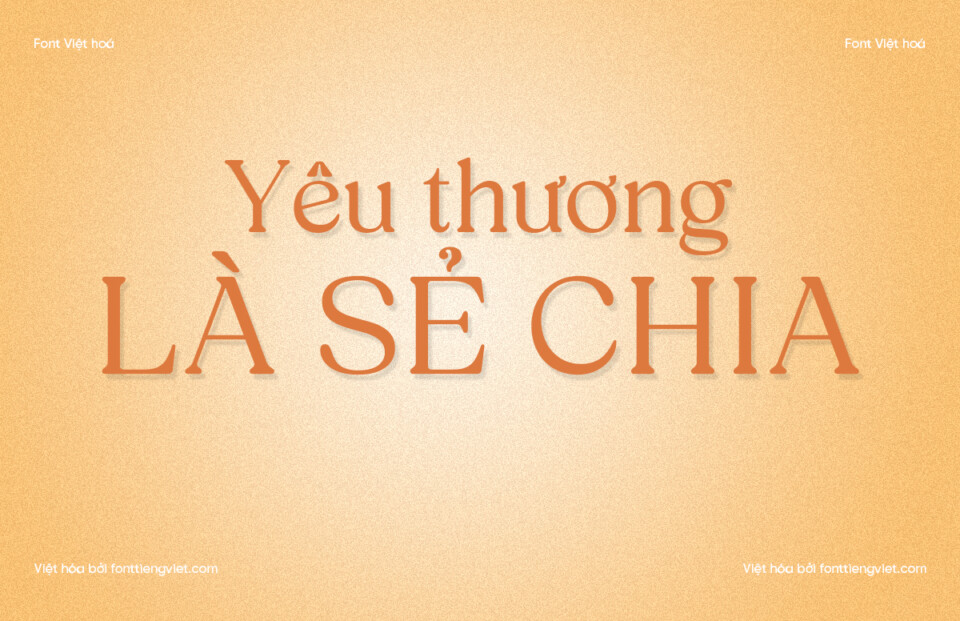
Font Việt hóa 1FTV VIP Brado Quena
Trong thế giới đồ họa hiện đại, việc lựa chọn một bộ font chữ phù hợp đóng vai trò quyết định đến linh hồn của tác phẩm. Đặc biệt đối với các nhà thiết kế tại Việt Nam, nhu cầu tìm kiếm các bộ font đã được tinh chỉnh dấu tiếng Việt là vô cùng lớn. Font Việt hóa 1FTV VIP Brado Quena xuất hiện như một giải pháp hoàn hảo, mang đến sự kết hợp tinh tế giữa nét cổ điển và hơi thở đương đại. Nếu bạn đang tìm kiếm một Font Miễn Phí để làm mới kho tài nguyên sáng tạo của mình, thì đây chính là lựa chọn không thể bỏ qua. Bộ font này không chỉ hỗ trợ đầy đủ bảng mã tiếng Việt mà còn giữ trọn vẹn đường nét thanh thoát của thiết kế gốc, giúp các văn bản trở nên chuyên nghiệp và bắt mắt hơn bao giờ hết.
Khám phá vẻ đẹp độc đáo của Font Việt hóa 1FTV VIP Brado Quena
Bộ font này thuộc nhóm Serif (phông chữ có chân) với những đường nét được chăm chút tỉ mỉ. Điểm nhấn của 1FTV VIP Brado Quena nằm ở sự cân bằng giữa độ dày và độ mỏng của các nét chữ, tạo nên cảm giác sang trọng nhưng vẫn rất dễ đọc. Khi được Việt hóa bởi đội ngũ 1FTV, các ký tự đặc biệt như ă, â, đ, ơ, ư cùng hệ thống dấu thanh được đặt ở vị trí tối ưu, tránh tình trạng bị đè nét hay lệch khoảng cách thường thấy ở các font chưa qua chỉnh sửa.
Ứng dụng đa dạng trong nhiều lĩnh vực thiết kế
Nhờ vẻ ngoài lịch lãm, Font Việt hóa 1FTV VIP Brado Quena thường được ưu tiên sử dụng trong các thiết kế nhận diện thương hiệu cho các khách sạn cao cấp, spa, hoặc các nhãn hàng thời trang. Bên cạnh đó, các bạn học sinh và giáo viên cũng có thể ứng dụng font này vào việc làm slide bài giảng, thiệp mời hoặc trình bày tiểu luận để tạo ấn tượng thị giác mạnh mẽ. Sự đa dụng này giúp font chữ chiếm được lòng tin của cộng đồng thiết kế Việt trong suốt thời gian qua.
Tại sao bạn nên sở hữu Font Việt hóa 1FTV VIP Brado Quena ngay hôm nay?
Lý do đầu tiên chính là khả năng hiển thị xuất sắc trên cả màn hình kỹ thuật số và bản in. Các nét chân chữ được thiết kế sắc sảo giúp văn bản giữ được độ nét dù ở kích thước nhỏ hay lớn. Thứ hai, việc sử dụng các bản Việt hóa chuẩn giúp tiết kiệm đáng kể thời gian căn chỉnh dấu thủ công. Thay vì phải tự vẽ thêm dấu cho từng ký tự, bạn chỉ cần gõ nội dung và tận hưởng thành quả đẹp mắt ngay lập tức. Đây là yếu tố cực kỳ quan trọng đối với những người làm nghề thiết kế bận rộn.
Kết luận về bộ Font Việt hóa 1FTV VIP Brado Quena